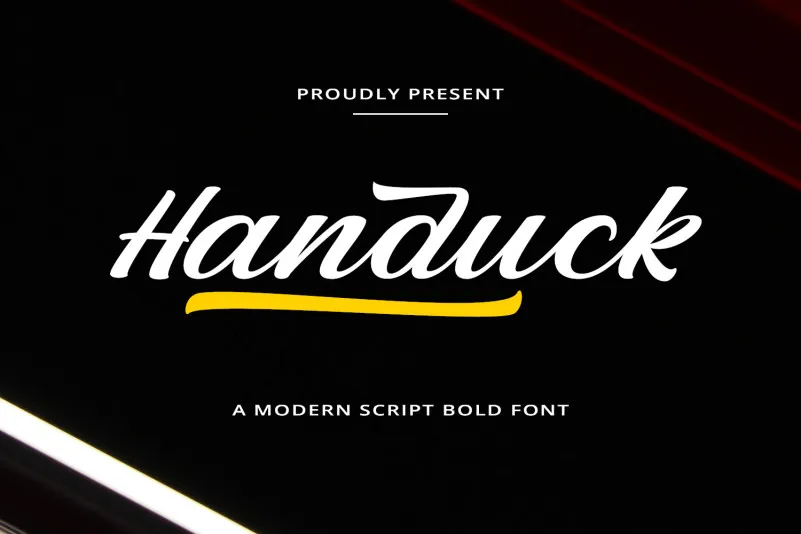
Handuck Font – Download Grátis
Esta é uma encantadora e grossa fonte escrita a mão, polida e deslumbrante, projetada para dar um toque elegante aos seus headlines e logotipos. Obrigado à Icreatype por criar essa font que transmite poder, confiança e dinamismo. Ela é perfeita para adicionar um caráter nostálgico a seus designs, adicionando uma pitada de memória vivida às suas criações digitais. Seja em um projeto de jornalismo editorial ou em seu próximo design gráfico, essa fonte certamente enriquecerá sua visão e dará vida aos seus projetos.